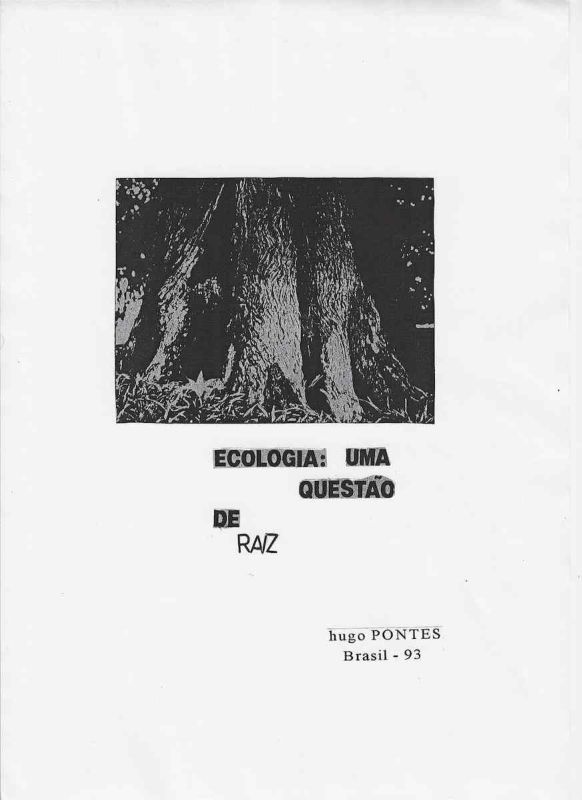
Hugo Pontes, Ecologia: uma questão de raiz, 1993, impressão gráfica, Brasil. Obra de poesia visual e arte conceitual que articula fotografia, tipografia e linguagem verbal em torno da temática ecológica.
TEXTO SALSA EM PORTUGUÊSHugo Pontes, Ecologia: uma questão de raiz, 1993, impressão gráfica, Brasil. Obra de poesia visual e arte conceitual que articula fotografia, tipografia e linguagem verbal em torno da temática ecológica. A composição apresenta a imagem fotográfica em preto e branco da base de uma árvore, com destaque para o tronco, a textura da casca, o solo e a região das raízes. Abaixo da fotografia aparece a expressão Ecologia: uma questão de raiz, organizada espacialmente em diferentes linhas e com variações tipográficas. As palavras Ecologia, Uma, Questão e De aparecem em caracteres de forte peso visual, enquanto Raiz recebe tratamento gráfico distinto, semelhante à escrita manual. A disposição das palavras fragmenta a frase e transforma sua leitura em construção espacial. O termo raiz funciona simultaneamente em sentido literal, relacionado à estrutura vegetal representada na fotografia, e em sentido metafórico, indicando origem, fundamento e causas profundas das questões ambientais. A relação direta entre imagem e palavra produz uma reflexão sobre natureza, preservação ambiental, responsabilidade ecológica e as origens dos problemas ambientais. A obra é identificada na própria impressão com o nome Hugo Pontes, Brasil e a indicação 93, correspondente a 1993. Ecologia: uma questão de raiz integra a produção de Hugo Pontes relacionada à poesia visual brasileira, poesia experimental, arte ecológica, fotografia, comunicação visual, consciência ambiental, linguagem gráfica e relações entre texto e imagem.SALSA TEXT IN ENGLISHHugo Pontes, Ecology: a question of roots, 1993, graphic print, Brazil. A work of visual poetry and conceptual art combining photography, typography and verbal language around an ecological theme. The composition presents a black and white photographic image of the base of a tree, emphasizing the trunk, the texture of the bark, the ground and the root area. Below the photograph appears the expression Ecology: a question of roots, spatially arranged across different lines and using typographic variations. The words Ecology, A, Question and Of are presented with strong visual weight, while Root receives a distinct graphic treatment resembling handwriting. The arrangement of the words fragments the sentence and transforms reading into a spatial construction. The term root operates simultaneously in a literal sense, referring to the plant structure represented in the photograph, and in a metaphorical sense, suggesting origin, foundation and the deeper causes of environmental problems. The direct relationship between image and word creates a reflection on nature, environmental preservation, ecological responsibility and the origins of ecological issues. The work is identified in the print itself with the name Hugo Pontes, Brazil and the indication 93, corresponding to 1993. Ecology: a question of roots is part of Hugo Pontes production associated with Brazilian visual poetry, experimental poetry, ecological art, photography, visual communication, environmental awareness, graphic language and relationships between text and image.
TEXTO DE OBSERVAÇÃO EM PORTUGUÊSImpressão gráfica de Hugo Pontes datada de 1993 e identificada na própria obra pela inscrição hugo PONTES, Brasil, 93. A parte superior da composição apresenta fotografia em preto e branco mostrando em enquadramento aproximado a base de uma árvore de grande porte. O tronco domina o campo fotográfico e evidencia superfícies irregulares, volumes, fendas e texturas da casca, enquanto a vegetação e o solo aparecem junto à base. Abaixo da fotografia encontra se a frase Ecologia: uma questão de raiz, distribuída de maneira não convencional pela página. Ecologia e Uma aparecem lado a lado na primeira linha, Questão surge abaixo, De é deslocado para a esquerda e Raiz aparece em posição inferior com grafismo diferente das demais palavras. Essa organização introduz ritmo, pausa e deslocamento visual na leitura, característica da poesia visual e da experimentação tipográfica. A palavra raiz estabelece uma conexão imediata com a fotografia da árvore e cria um jogo semântico entre a raiz física do vegetal e a ideia de investigar a raiz de uma questão. A obra utiliza poucos elementos, fotografia, texto e espaço branco, produzindo uma mensagem direta sobre ecologia e sobre a necessidade de compreender os fundamentos dos problemas ambientais. O contraste entre a imagem natural e a estrutura tipográfica reforça o caráter comunicacional e conceitual do trabalho. Documento relevante para pesquisas sobre Hugo Pontes, poesia visual no Brasil, arte ecológica, ecologia na arte, poesia experimental brasileira, fotografia e poesia, comunicação ambiental, tipografia experimental e práticas artísticas dedicadas à relação entre natureza, linguagem e consciência ecológica.OBSERVATION TEXT IN ENGLISHGraphic print by Hugo Pontes dated 1993 and identified within the work by the inscription hugo PONTES, Brazil, 93. The upper part of the composition presents a black and white photograph showing a close view of the base of a large tree. The trunk dominates the photographic field and reveals irregular surfaces, volumes, fissures and bark textures, while vegetation and ground are visible around its base. Below the photograph appears the phrase Ecology: a question of roots, distributed across the page in an unconventional arrangement. Ecology and A appear together on the first line, Question is positioned below, Of is displaced toward the left and Root appears at a lower level with a graphic treatment different from the other words. This arrangement introduces rhythm, pause and visual displacement into the act of reading, characteristics associated with visual poetry and typographic experimentation. The word root establishes an immediate connection with the photograph of the tree and creates a semantic interplay between the physical root of a plant and the idea of investigating the root of a question. The work employs few elements, photography, text and white space, producing a direct message about ecology and the need to understand the foundations of environmental problems. The contrast between the natural image and the typographic structure reinforces the communicational and conceptual character of the work. A relevant document for research on Hugo Pontes, visual poetry in Brazil, ecological art, ecology in art, Brazilian experimental poetry, photography and poetry, environmental communication, experimental typography and artistic practices devoted to the relationship between nature, language and ecological awareness.
Hugo Pontes, Ecology: a question of roots, 1993, graphic print, Brazil. A work of visual poetry and conceptual art combining photography, typography and verbal language around an ecological theme.